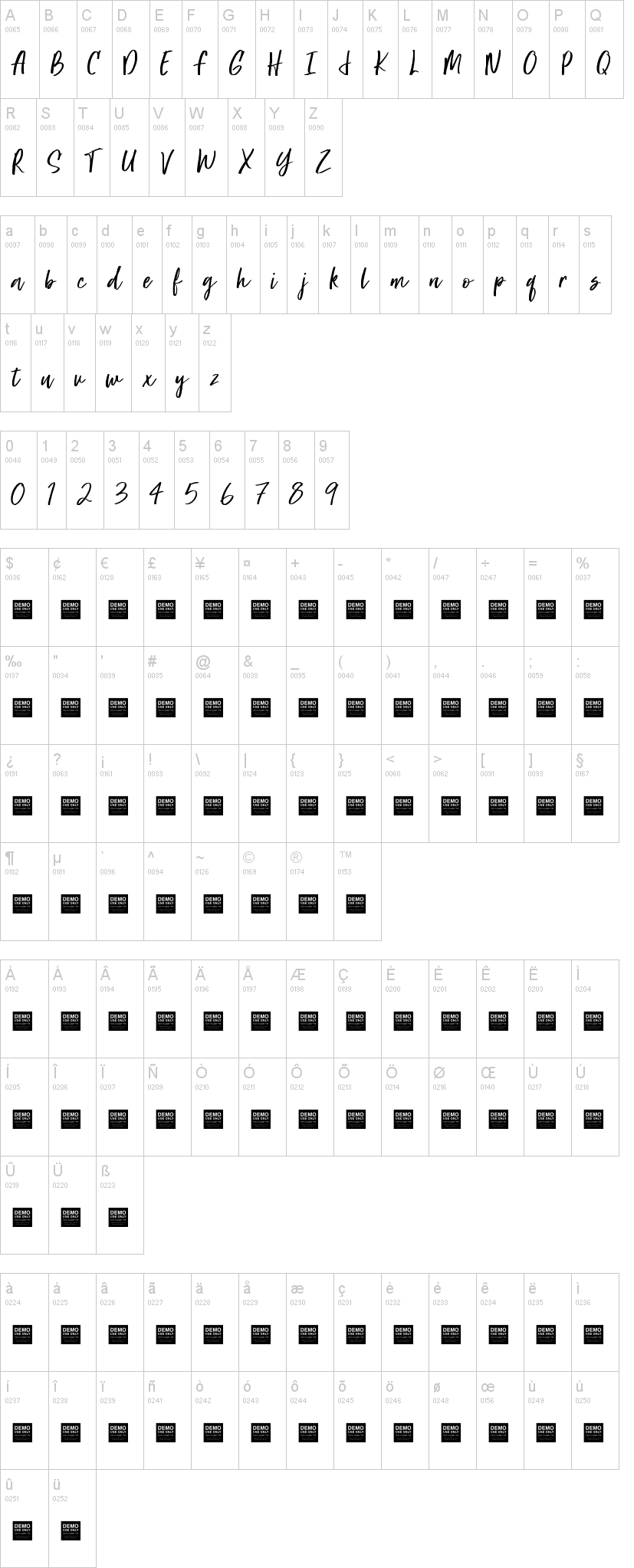
Super Natural 是一款由丹麦设计师 Jonas Hecksher 创作的新字体,它是一款极具视觉冲击力的自然风格字体,具有清晰的线条和自然的流畅性,适用于大多数设计项目。Super Natural 字体具有超高的可读性,适合用于报纸、杂志、海报等文字排版。它有助于提升文字的可读性,并且能够为设计师提供多样化的文字设计效果。内容介绍
Super Natural是一款非常不错的手写艺术字体,具有很好的视觉感,适合于文化类的宣传设计、商业类品牌的广告和产品包装设计以及个性化文字排版等较多场景。